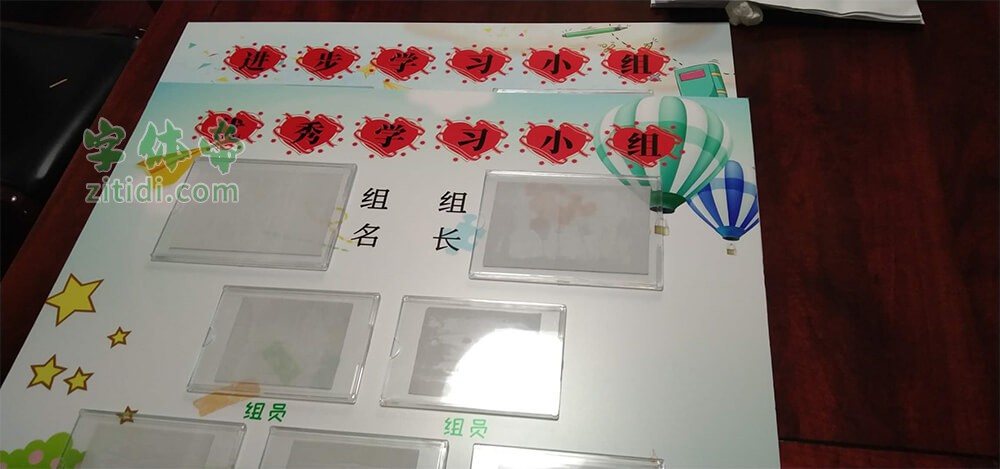
思源宋体花样心纹是在“思源宋体 粗体”基础上提取英文与符号共123个字形,汉字6763个常用字修改而成,所谓花样字体,笔者自定义为:给常规字形加一些修饰花纹效果。本次共享的花样字体只对6763个汉字添加花纹,英文与符号保持原字形不变,大部分花样字体并不适用于大篇幅的文章使用,主要作用于标题或一些特殊场合,如图片水印等等。
这款字体的作者和最初出处我没有找到,但我猜应该是@五源设计做的。我为什么会猜是@五源设计做的呢?因为只要你输入“·”这个字符,看到的是@五源设计的LOGO和二维码,哈哈,这是个彩蛋吗?
“思源宋体花样心纹”是一款书写很新颖的字体,字体大方,适合各种设计作品使用!欢迎下载!